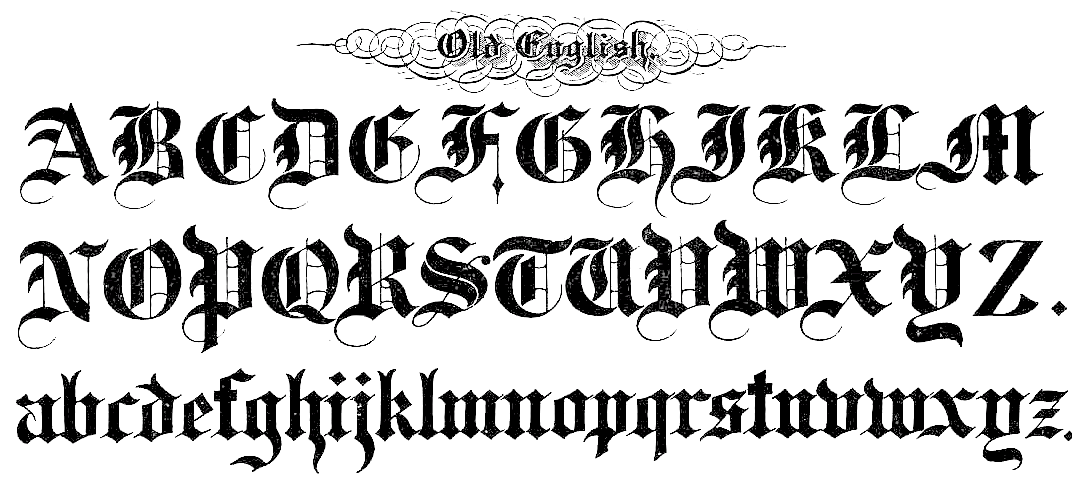
Готические шрифты. Вы когда-нибудь задумывались, как толпа добавляет буквы адаптировались в своих социальных сетях? Если вы использовали в Instagram, Twitter, Facebook, WhatsApp или Tik TokВы знаете, что существует не так много альтернатив, когда дело доходит до настройки писем, поскольку биография, комментарии, подписи … имеют уже установленный источник.
Нет альтернативы олицетворению Тип букв, шрифты, символы и Символы и трансформируйте их, сделав более эстетичным, в соответствии с вашими интересами. Впрочем, не беспокойтесь! Вы все еще можете использовать Готические шрифты приятно и интересно через это преобразователь.
🚀 Готические шрифты, гарнитуры и шрифты
Используйте готические шрифты, С этим конвертер текстов песен вы можете составлять буквы, шрифты, символы и необычные символы для ваших фраз из социальных сетей (Instagram, TikTok …), используйте отличные буквы в статусе WhatsApp или Fb и используйте
Пришло время заняться чем-то другим, тебе не кажется? Настройте биографию профиля или выделите части подписей к изображениям и видео, которые вы публикуете. Изменяет обычный текст в разных стилях Готические шрифты, например шрифты для татуировок, каллиграфические шрифты, веб-скрипт, курсив, письменные источники от руки, уникальные символы, буквы, шрифты, гарнитуры, символы и символы или красиво.
В различных социальных сетях используется шрифт, который лучше всего адаптируется к общему дизайну системы. Это часть единообразия, необходимого для визуального благополучия потребителей, просматривающих эти платформы.
Оказывается, есть способ вставить пользовательские буквы для копирования и вставки которые, безусловно, являются единичными персонажами, например emojis и другие символы. На практике они отображаются как адаптированные шрифты, но технически они называются Символы Юникода.
🎯 Готические шрифты для копирования и вставки
Готические шрифты для копирования и вставки. Мы можем резюмировать, что с конвертером букв вы на самом деле не получаете сами шрифты, поскольку они являются символами Unicode, эти коды могут иногда
Например, ввод текста в поле вверху приведет к список символов и красивые буквы скопировать и вставить. То, что вы видите на своем устройстве, может показаться странным при использовании других устройств. Это происходит из-за того, что устройства разных жанров по-разному интерпретируют эти символы Unicode или еще не поддерживают эти символы.
Это не означает, что в этом инструменте есть ошибка, это означает, что шрифт, выбранный для использования на сайте, не поддерживает этот символ. Однако есть группа персонажей, которые, если их адаптировать к дизайну и стилю, например: курсив, жирный шрифт и т. д. поскольку они являются специальными символами Юникода и не зависят от шрифтов, вы сможете скопируйте и вставьте их, и используйте их в своей биографии или комментариях в Tumblr, Twitter, Fb, Instagram, Whatsapp, TikTok и т. д.
✍ Конвертер готических шрифтов
Примеры, созданные с помощью генератора готических шрифтов
ℌ𝔢𝔩𝔩𝔬
𝕳𝖊𝖑𝖑𝖔
♖☝ ђ𝕖Ⓛ𝕝𝕠 💘
👹 𝓗𝓮𝓵𝓵𝓸
𝐻𝑒𝓁𝓁𝑜
ℍ𝕖𝕝𝕝𝕠
привет
🎀 𝐻𝑒𝓁𝓁🏵 🎀
🐣 ʜᴇʟʟᴏ
ollǝH
🅷🅴🅻🅻🅾
˜ ”* ° • .
˜” * ° • Привет • ° * ”˜. • ° *” ˜
H҉e҉l҉l҉o҉ ☆
🎈 ᕼ𝐞ℓ𝓵Ⓞ ♞ඏ
🐤🐳 卄 𝐞ℓ ㄥ ᗝ 💣💢
→ Код Unicode: что это такое?
Что такое Юникод? Это Международный стандарт который позволяет компьютерам (и другим устройствам) интерпретировать и использовать текстовые символы из любой системы письма.
Unicode Он был разработан для решить проблему, вызванную огромным существованием кодовых групп. С самого начала программирования разработчики использовали свои языки, поэтому перенос текста с одного компьютера на другой часто приводил к потере информации.
Unicode принес большие жертвы в 80-х, чтобы
El Стандарт Unicode может отображать шрифты и символы сотрудники на любом языке; включая смайлики, которые также являются текстовыми символами.
Итак, с этим конвертером Готические шрифты не создавать источники, но Символы Unicode что вы можете использовать в Instagram, Twitter, Pinterest, Fb, Tumblr, WhatsApp, TikTok… Когда вы получите стиль шрифта, который вам больше всего нравится, вам просто нужно скопировать и вставить его в любом месте.
➕ Текстовые шрифты
Первый сто двадцать восемь символы из списка Unicode являются наиболее часто используемыми, и он известен как алфавит ASCII. Алфавит ASCII содержит буквы, десятичные цифры, знаки препинания и некоторые особые символы.
Тем не менее, ASCII не обращается к знакам с диакритическими знаками, вопросительным знакам или некоторым другим символам (математическим, греческие буквы,…) Это актуально в разных контекстах.
Ширина пера соответствует штрихам вниз, что создает впечатление солидности, но вместо этого закругленная кривая вверху буквами типа m и n , образует изогнутый угол на вершине.Восходящий штрих этой кривой тонкий, а нисходящий — толстый. Этот заключает серию ровных арок:
Изогнутые и изогнутые буквы резко наклонены вверху, особенно b и p , но снизу все еще закруглены, который придает замкнутому пространству миндалевидную форму или форму слезинки, а отдельные буквы выглядят так, как будто они слегка наклонены назад: